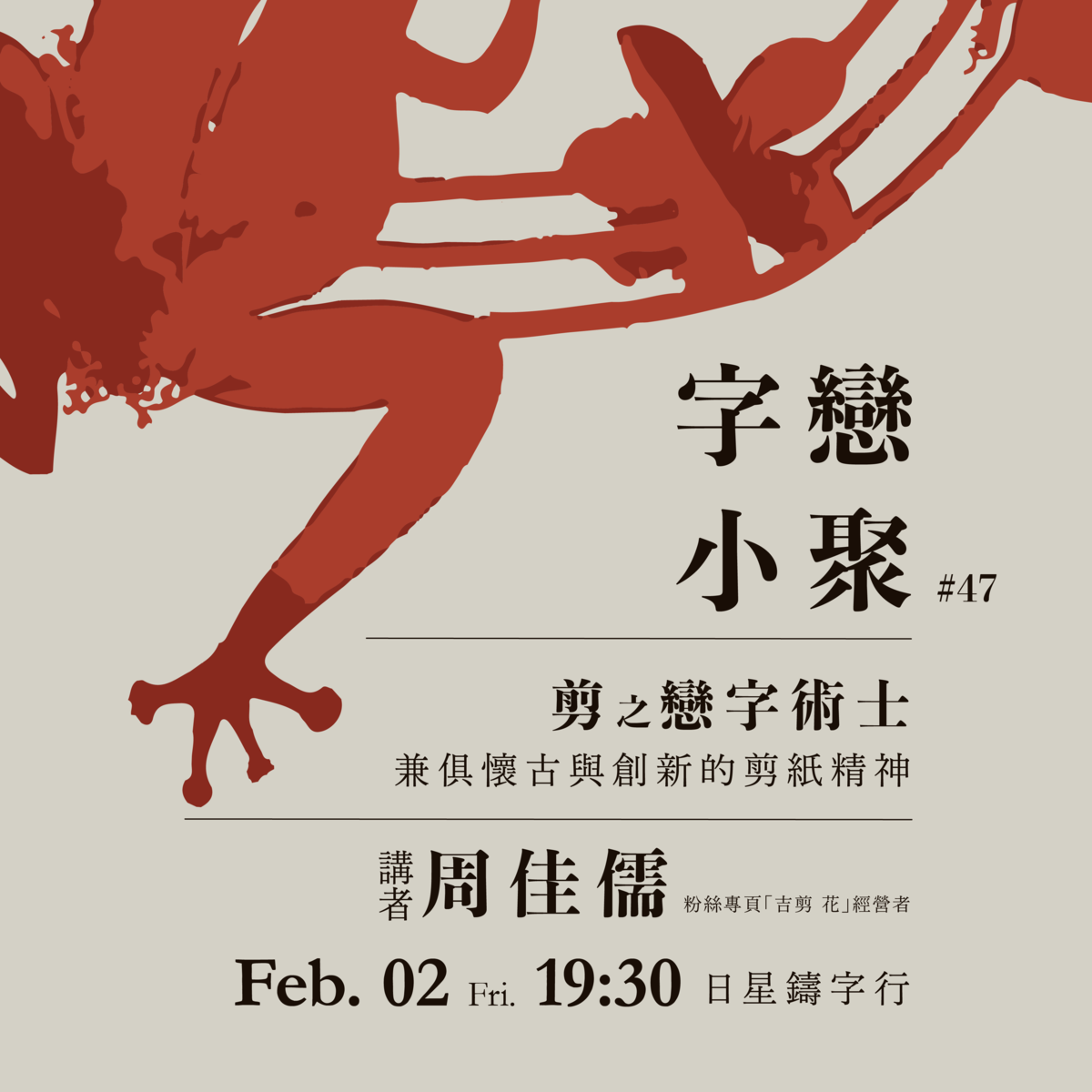
往年,春節前夕的字戀小聚都要寫書法應個景。但這一次我們換個口味,來體驗剪紙藝術。為什麼這跟字有關係呢?不論是已故的字型設計大師 Adrian Frutiger,或是在台灣有高知名度的字型設計師小林章,都提過他們日常的一大業餘興趣便是剪紙。
剪紙與字體設計其實有異曲同工之妙,其美感都來自於對於輪廓形狀、黑白空間佈局的掌握。因此這次除了過年應景以外,也讓大家透過不同的工具與方法,練習探索相同於字體設計的美感。
講者
周佳儒(粉絲專頁 吉剪 花 經營者)
創作風格:
學生時期便開始與藝術結緣。透過時間的摸索,慢慢找尋適合創作的最佳方式。
近期以剪紙為主要的創作方式,起因是因想送外國友人一份有文化又特別的禮物,沒
想到卻愈剪愈有興趣,便開始以「剪紙」為主的創作歷程,並在紙張的世界裡尋求紙
的可能性,利用「紙」的可大可小、反覆繁複、平面立體…等特性,做出多樣的發展
,如同我們生活中存在的無限可能性一般讓人玩味。希望藉由剪紙,傳遞愉悅的心情
給大家,用美好、正面的態度去接待生活中的大小事,透過作品推廣懷古創新的剪紙
精神,讓更多人體驗剪紙的不同風貌~